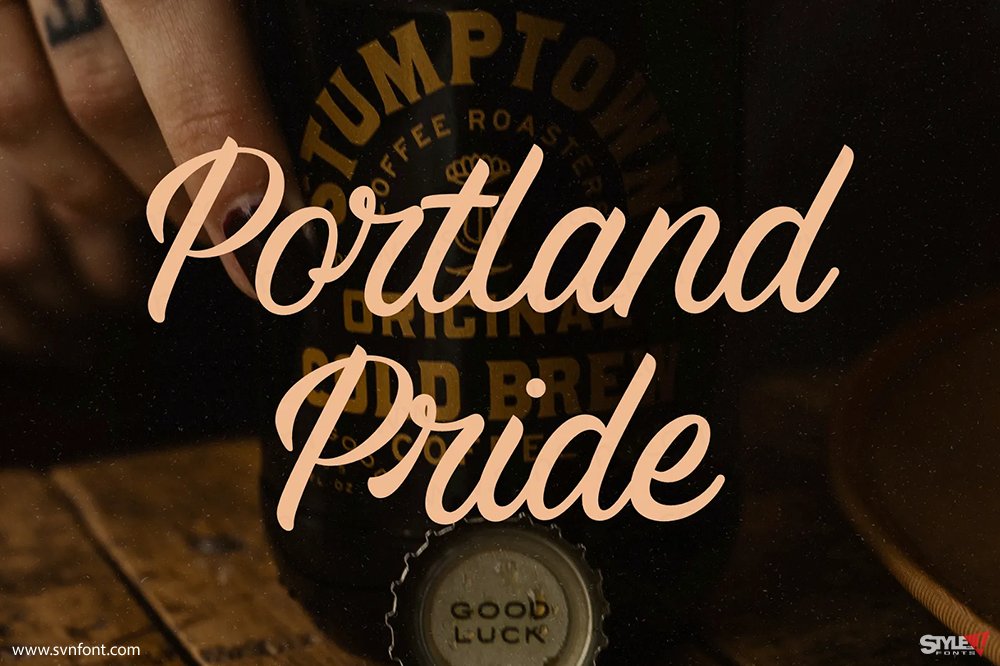
Alluring Fonts – Modern Calligraphy là một kiểu chữ giản dị và thanh lịch, giúp chữ viết tay trông tự nhiên. Font chữ nhẹ nhàng này có các nét nối (ligatures), ký tự thay thế (alternate characters), một loạt dấu câu và chữ số, cùng với dấu phụ và hỗ trợ đa ngôn ngữ thông qua việc sử dụng các ký tự tiếng nước ngoài.
Font hiện đại này được thiết kế để mô phỏng vẻ ngoài của chữ viết tay thật. Nó rất phù hợp để sử dụng trong các tiêu đề vì hình thức đơn giản và cấu trúc không phức tạp.
Hoàn hảo cho các dự án xây dựng thương hiệu, logo, thiết kế đám cưới, bài đăng trên mạng xã hội, quảng cáo, bao bì sản phẩm, thiết kế sản phẩm, nhãn mác, nhiếp ảnh, hình mờ, thiệp mời, văn phòng phẩm và bất kỳ dự án nào cần phong cách viết tay.
Nhà thiết kế: 50Fox Team
Nhà phát hành: 50Fox Team